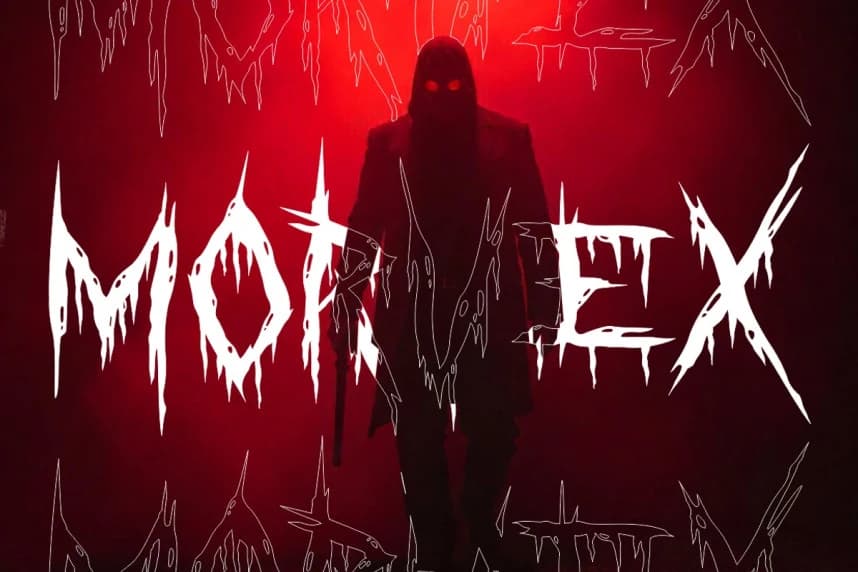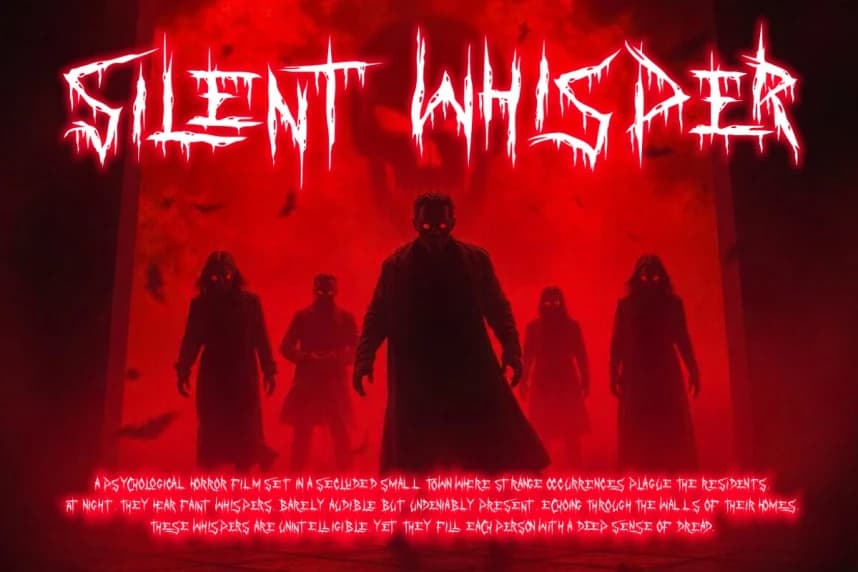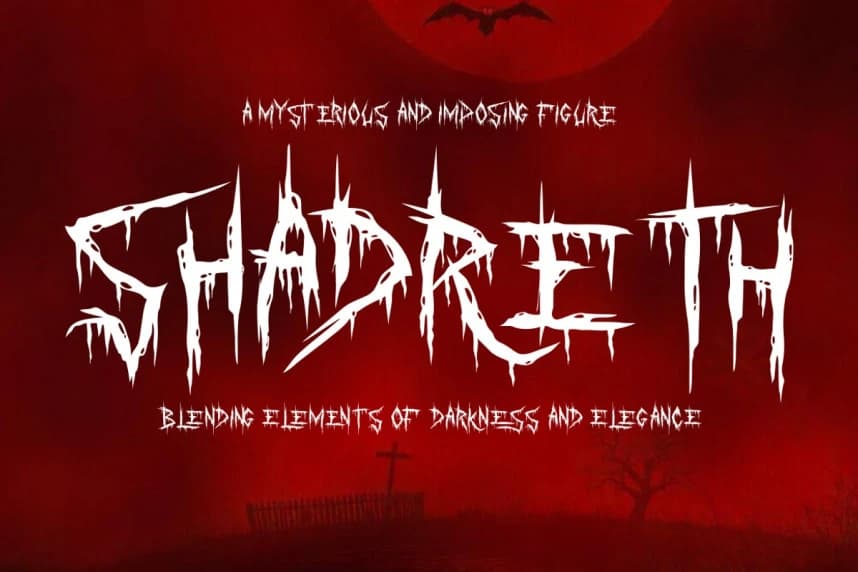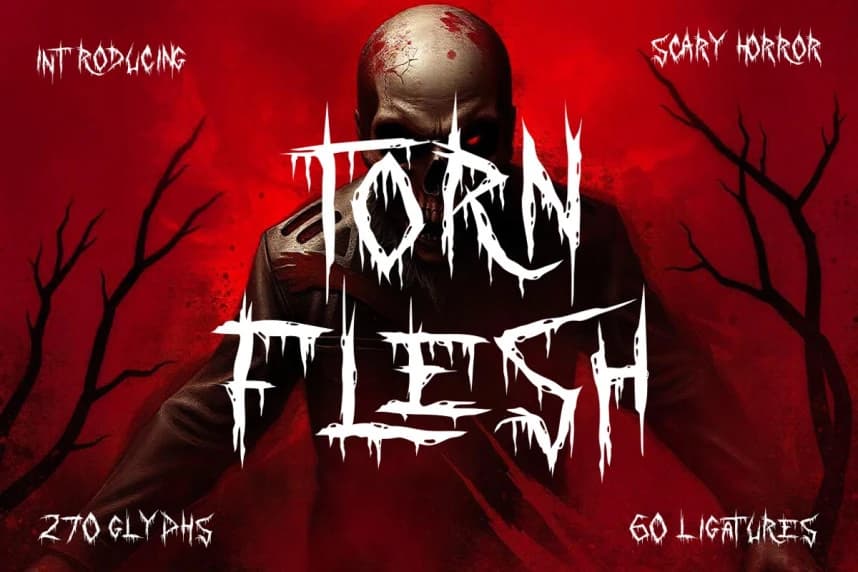
Torn Flesh Font
Torn Flesh Font - Scary Horror Font, dehşet ve gerilimi uyandırmak üzere tasarlanmış ürkütücü bir yazı tipi. Bu yazı tipinin çentikli ve yıpranmış harfleri pençe izlerine benzer ve korku temalı tasarımlar için iğrenç, el ile yırtılmış görünüm gerektiğinde mükemmeldir.
Torn Flesh Font - Scary Horror Font, korku ve gerilimi uyandırmak için tasarlanmış ürpertici bir yazı tipi. Bu yazı tipinin keskin ve yıpranmış harfleri tırnak izlerini andırır ve bu nedenle korku temalı tasarımlar için iğrenç, elle yırtılmış bir görünüm sağlar.